宋体也可以设计的很漂亮
为什么人人都爱宋体字?是什么样的魔力让宋体字集万千宠爱于一身?本期将为大家探秘宋体字,和以往文章一样,还是以理清思路、探究重点、坑点为原则,本期特意制作了四个宋体案例,相信实例相辅定能为你解惑答疑。
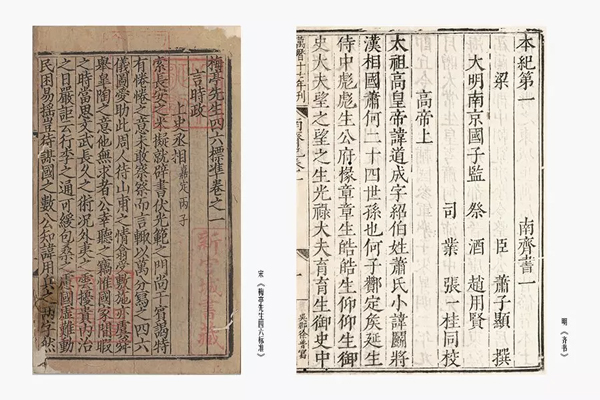
图一 左:宋 《梅亭先生四六标准》 右:明 《齐书》
我们先简单了解一下宋体字的身世,事实上宋体字的叫法明朝时期才出现。因明朝文人极度推崇“宋刻本”,明代出版界便多翻刻宋刻本,但并非原汁原味楷味浓厚的宋字,而是经过一定的“简化”,最终形成了专门用于印刷的字体。在康熙十二年文献中规定:“此后刻书,凡方体称宋体字,楷书均称软字”。“宋体”之名由此而来。
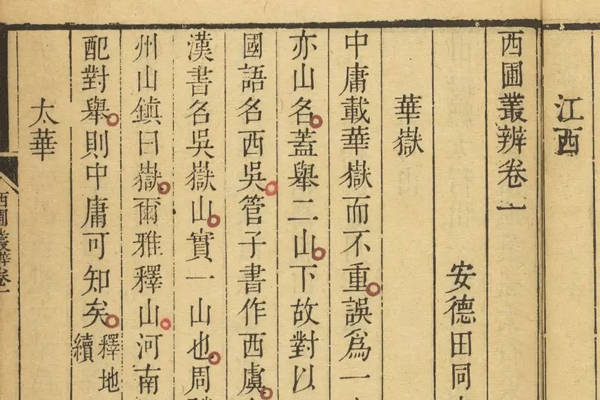
图二 清 乾隆时期刊本《西圃丛辨》
图一中的对比很明显的可以看到宋朝和明朝刻本中书体的变化,明朝时期的印刷字更接近我们现在熟悉的样子,到清乾隆时期,宋体字大体定型,与现代宋体基本相同(图二)。
了解完一段历史再看现代宋体字,之所以人人爱宋体字我想是因为每个笔画都是穿越千年的历史,再怎么变都有根。
由左到右:楷体、宋体、黑体
宋体颜值高想做好自然不是易事,笔画中的体饰特点虽明显,但实在不好把控,这也就是为什么建议新手从等线字型入手。那么想要做好宋体字究竟应该怎么做?下面,我特意做了四个不同风格的(泛)宋体字,希望以字体风格为划分点聊聊宋体字,不保证看完此篇文章你能立刻上手,但我相信会让你对宋体字有更清晰的认识,爱上宋体更多一点。
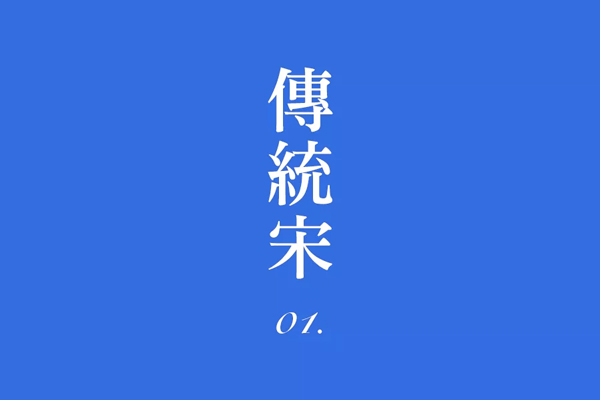
一、传统宋
想要做好宋体字就必须要了解宋体字的基本笔画特点,仅凭眼睛看其实难以全面深刻的了解,虽然市面上有很多种类的宋体字,但细细观察大同小异,可以选择一些偏传统的宋体字进行临摹学习,因为风格传统的宋体字基本上保留下所有宋体笔画该有的特点。
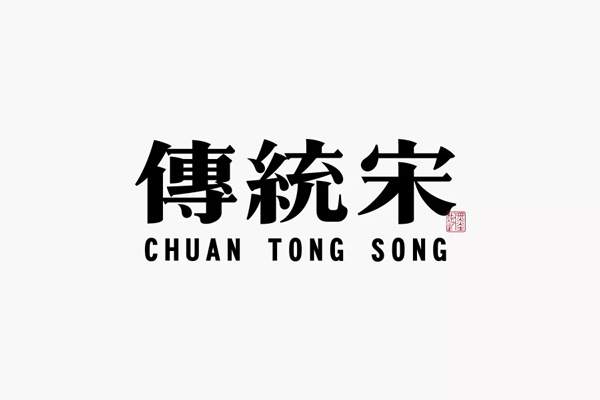
传统宋结构端正、规整,笔画横细竖粗,细节变化丰富细腻,像一位知识渊博的长者。可以观察上图做的这组字,偏向传统,比较厚实,该类风格的字型难点有二:一个是笔画处理要得体,在一个是结构空间要严谨。
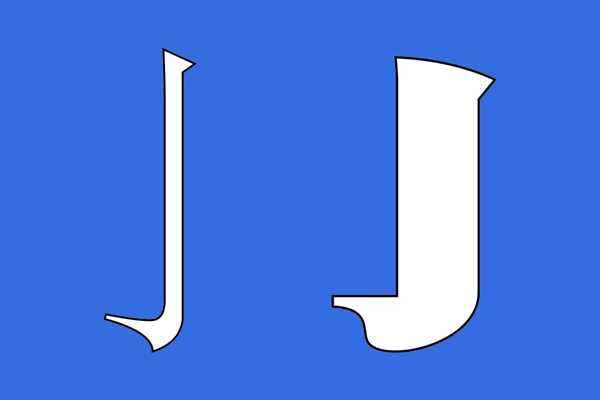
a.笔画处理
不像一些黑体字的笔画横平竖直,宋体字笔画的转折是非常多的,为什么很多人做的宋体字不好看?很大一部分原因就是基础笔画处理的不讲究,比如常见的问题:体饰比例不协调、转折线条不流畅、走势不流畅等等。一个个笔画就像是零部件,只有每个零部件合格了,拼到一起再能完美运行。
上图左是字库内宋体字的竖勾,右边是我做的那组字中的竖勾,几乎是一个模子刻出来的,但又可以说变化挺多,传统宋也并不是照搬之前的一套,也可以有变化。做宋体字可以先把基础的笔画一般是:横、竖、撇、捺、点先做出来备用。
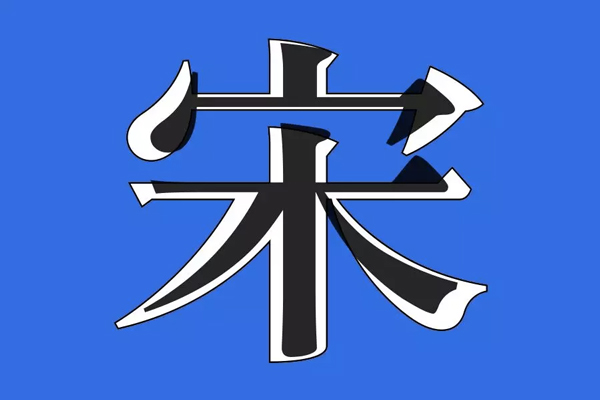
b.结构空间
参照字库内的一些宋体字的结构空间绝对是简直不能再简单有效的方法了!宋体字的框架结构相对固定,就像上面图片中黑色的为字库中的“明朝体”,下面白色字除了胖一点几乎是吻合的,说白了就等于换了下笔画;只需要把之前做好的基础笔画搭建起来,然后适当调整即可。
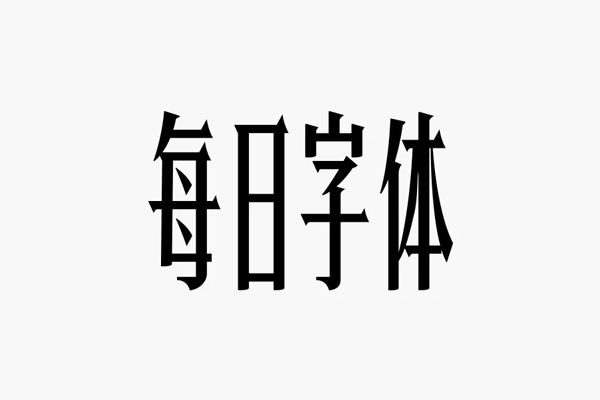
另外,结构主动压扁或抬高的处理,也能够让字增色不少,不妨试一下。上图文字结构明显是高的,同样的笔画如果做成“方块字”,个性或许不会这么凸显。
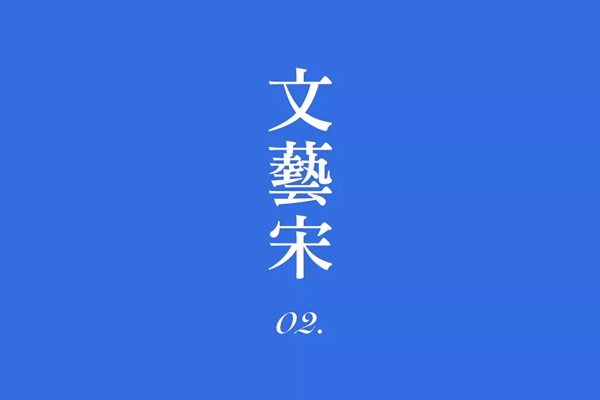
二、文艺宋
结构松而不散,透气开阔,笔画上收拾的更利落干净,宋体字也可以秒变文艺青年。很多笔画慢慢的像黑体字的状态去过渡,偶尔几处的笔画也会忍不住的冲出“边框”的束缚。
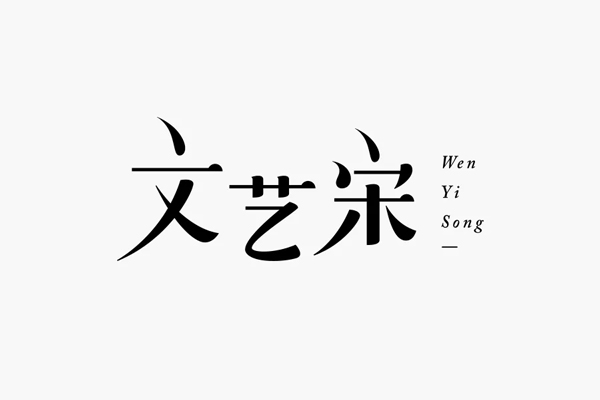
上面这组字显然更偏向女性化,所以一切“轻”处理。结构上并不像传统宋一些样严丝合缝,会故意把一些笔画断开,空间被打通留白变多,自然会给人比较“放松”的状态。
笔画有选择性的简化处理,这没有什么固定的范围,有时候甚至可以把西文中一些小特征用到文艺宋中,笔画的轻柔流畅,曲线居多,看起来更有弹性。
后会无期这组文艺的更有力量,相比上组曲线居多本组直角直线是主旋律,曲线只出现在撇捺笔画中,字面的大小差异随字体笔画、结构的不同而变,可以说是同样的文艺不同的气场。
三、萌萌宋
只听其名是不是已经被萌到了,没想到宋体还有这一面!我之前文章中说了好几种让字体变可爱的方式,其方式同样适用于此,只需要把笔画中融入一些宋体字的特征即可,说着好像挺简单,看下面我做的这组字。
这个绝不是最萌的状态,结构上还是显得拘谨一点,但好在笔画曲线居多,如果按照前面讲的标准为什么不是文艺的状态?前面讲到了另外一点是“轻”则体现出女性化,而本组字的笔画绝对算不是轻盈吧,就像婴儿肥一般憨态可掬。
同样的套路用到这组字中,你能够观察到具体哪些细节有变吗?笔画粗其实是相对的,一般还是遵循“横细竖粗”的宋字特点。
四、混搭宋
其实前面的字有些是介于宋体字和黑体字之间,区别是偏向宋体多一点罢了,这个混搭宋就是偏向黑体或许更多一些,把它归于宋体确实勉强了,但确实有很多朋友比较喜欢此类风格。
黑体+宋体+几何图形三者混到一起得如上字型,平时黑体字和宋体的结合不算新鲜,但如果再加入一点图形的点缀,会让整个作品更有装饰味,就更像是一个“叛逆少年”。
图形不必太复杂,基本的几何图形简单又好用。另外你也会注意到,以上每种不同的宋体我都会选配不同的拼音搭配,这个用好了绝对是最强辅助,好的版式能够字体作品更完整逼格更高!
混搭宋的规律其实很好找,一般撇捺点宋体走起,剩下的黑体或其他。
小结
字体设计从来就没有固定的套路,标题《百变宋》也绝非夸张,甚至过于保守,千万变化不为过。以上是我分四中常见风格为大家梳理的宋体字的,每一次写到最后我都号召大家动手尝试一番,因为看了那么多文章教程依然不会大有人在,可能不是文章写得不好,而是你没有行动起来!